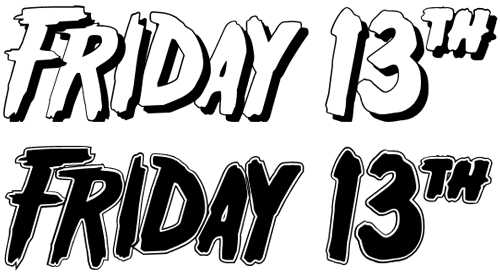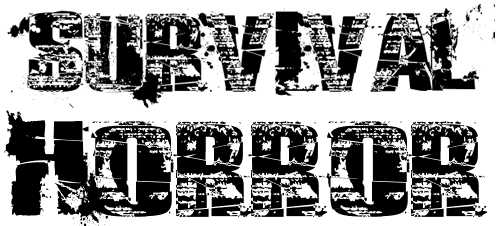
Демонические Шрифты, Death Metal Шрифты, Футуристичные и Индустриальные Метал Шрифты
MB Slavonic Minsk — Славянский Средневековый Металл Шрифт
Славянский языческий шрифт, отрисован вручную в Восточно-Европейском средневековом стиле, подходит для Folk Metal групп. Включает расширенный Латинский (Английский) алфавит, Кириллицу (Русский) и цифры. Бесплатный для частного использования, для коммерческого необходима ссылка на сайт автора. Создано: Сентябрь 2010
Шипованный, грубый, расколотый Шрифт в стиле надписей из Комиксов на тему ужасов. Включает расширенный Латинский (Английский) алфавит, Кириллицу (Русский) и цифры. 100% Бесплатный. Создано: Ноябрь 2010
Шрифт в стиле Поп-Арт и Граффити, гладкие края, жирный и хорошо читаемый. Я обычно не работаю в этом стиле, но захотелось попробовать что-то в необычном для себя стиле, и добавить разнообразия в мою коллекцию Металл Шрифтов. Включает расширенный Латинский (Английский) алфавит, Кириллицу (Русский) и цифры. 100% Бесплатный, ссылка на сайт автора приветствуется. Создано: Август 2010
Футуристический инопланетный шрифт с линиями и кругами. Создан для разнообразия в стиле шрифта текстов пришельцев для арта или интерфейсов, со своей яркой инопланетной индивидуальностью. Включает расширенный Латинский (Английский) алфавит и цифры. 100% Бесплатный, ссылка на сайт автора приветствуется. Создано: Май 2010
Брутальный и злобный Металл Шрифт, подходит также для дизайна в Black Metal стиле. Создан для использования в названиях и заголовках, так как не очень хорошо читаем в мелком размере. Включает расширенный Латинский (Английский) алфавит и цифры. 100% Бесплатный, ссылка на сайт автора приветствуется. Создано: Июль 2010
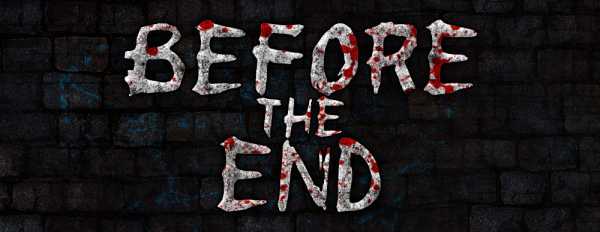
Рукописный, нацарапанный Metalcore Шрифт. Подходит для стилизации текста в пост-апокалиптическом стиле. Включает расширенный Латинский (Английский) алфавит, Кириллицу (Русский) и цифры. 100% Бесплатный. Создано: Август 2010
MB Poisoned Type — Футуристический, Инопланетный Шрифт
Зловещий разъеденный шрифт инопланетных пришельцев. Лучше всего выглядит с жидкими эффектами чем простой монохромный. Включает расширенный Латинский (Английский) алфавит, Кириллицу (Русский) и цифры. 100% Бесплатный. Создано: Август 2010
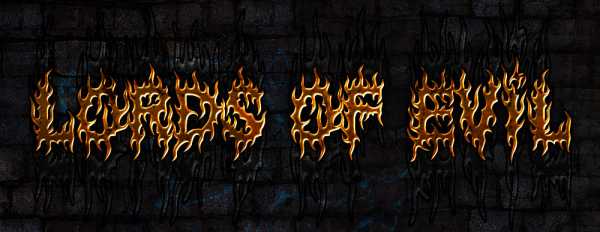
Демонический Black Metal Шрифт в стиле Diablo. Отрисован карандашом вручную. Включает расширенный Латинский (Английский) алфавит и цифры. 100% Бесплатный, ссылка на сайт автора приветствуется. Создано: Март 2010
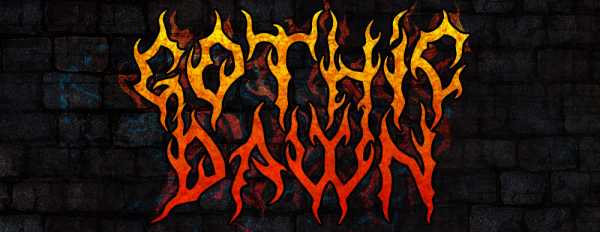
Современный готичный Металл Шрифт в крючковатом адском стиле, лучше детализирован чем более ранние шрифты. Hand-drawn with the Pencil. Включает расширенный Латинский (Английский) алфавит и цифры. 100% Бесплатный, ссылка на сайт автора приветствуется. Создано: 2009
Вручную нацарапанный Шрифт, стилизованный под рукопись Ведьмы. Хорошо читаемый в мелком размере и может быть полезен для оформления треклиста Metalcore группы. Включает расширенный Латинский (Английский) алфавит, Кириллицу (Русский) и цифры. 100% Бесплатный. Создано: Сентябрь 2010
Полностью бесплатный Death Metal Шрифт. Основная форма стилизована как косы Черной Смерти, Жнеца.
Используется группой: Wayfarer (Загреб, Хорватия). Отрисован вручную карандашом. Включает расширенный Латинский (Английский) алфавит и цифры. 100% Бесплатный, ссылка на сайт автора приветствуется. Создано: Апрель 2010
MB Back For Death — Расколотый Гранжевый Метал Шрифт
Разбитый, потрескавшийся Шрифт в стиле Гранж. Все края разъеденные и потертые, что делает шрифт давольно высоко детализированным, но все еще достаточно хорошо читаемый в мелком размере. Созданы как заглавные так и строчные буквы. Включает расширенный Латинский (Английский) алфавит, Кириллицу (Русский) и цифры. 100% Бесплатный. Создано: Январь 2010
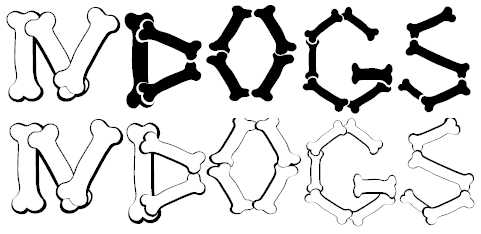
Стильный шрифт BN Manson Nights
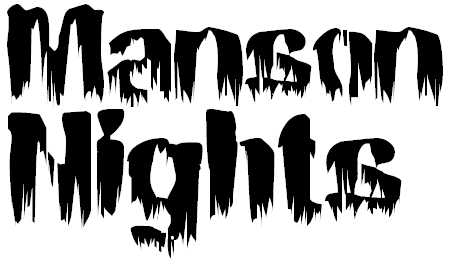
Шрифт в готическом стиле Amhole
Шрифт с узорами Vtks espinhuda
Прописной шрифт Gantz
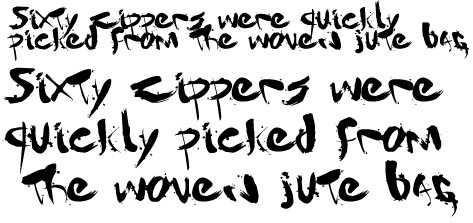
Шрифт от руки Last N Line
Готический шрифт Carsi
Обведенный шрифт Dzr Mental
Шрифт в виде набросков Psychotic
Размазанный шрифт Convalescence
Шрифт с потертостями и потеками Cocaine Sans
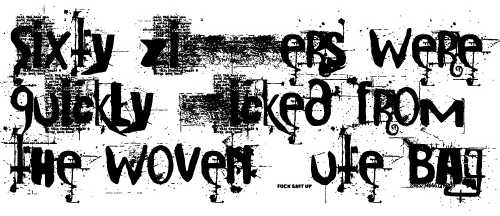
Почерканный шрифт Knife Fight
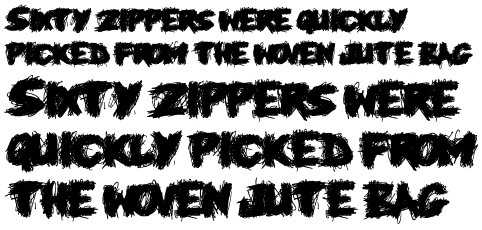
Грязный шрифт с пробелами Blasphemy
Жирный грязный шрифт El&font Block